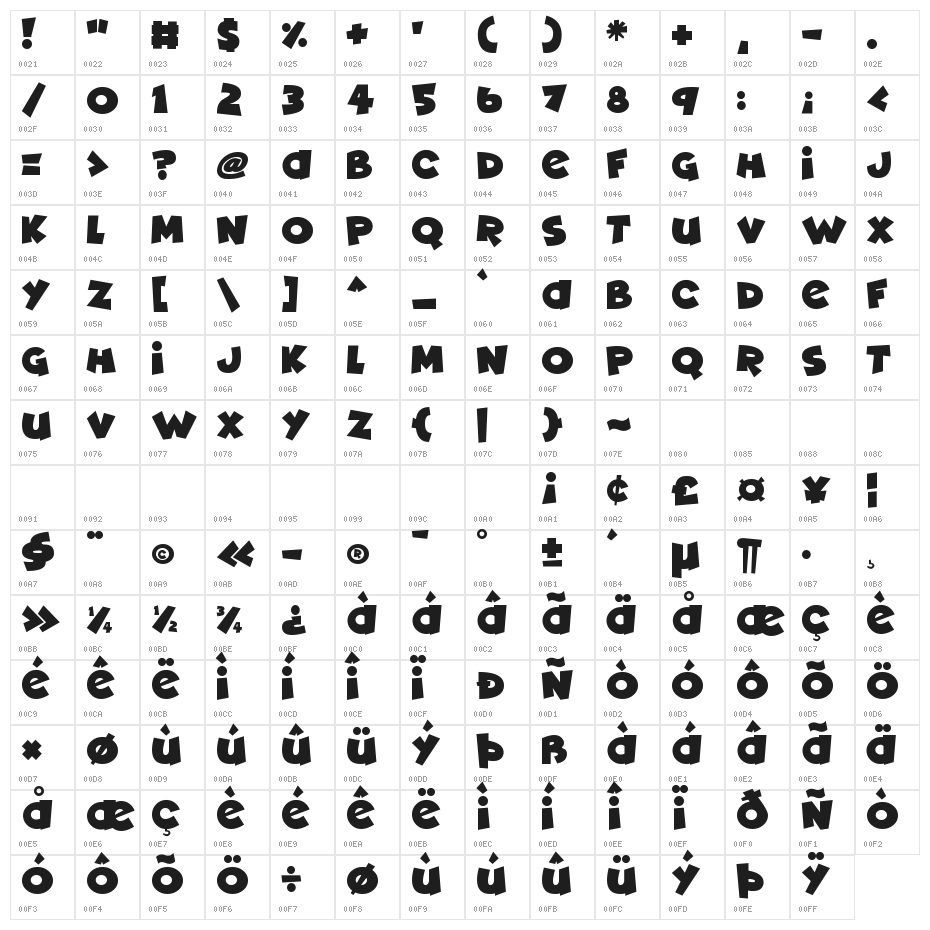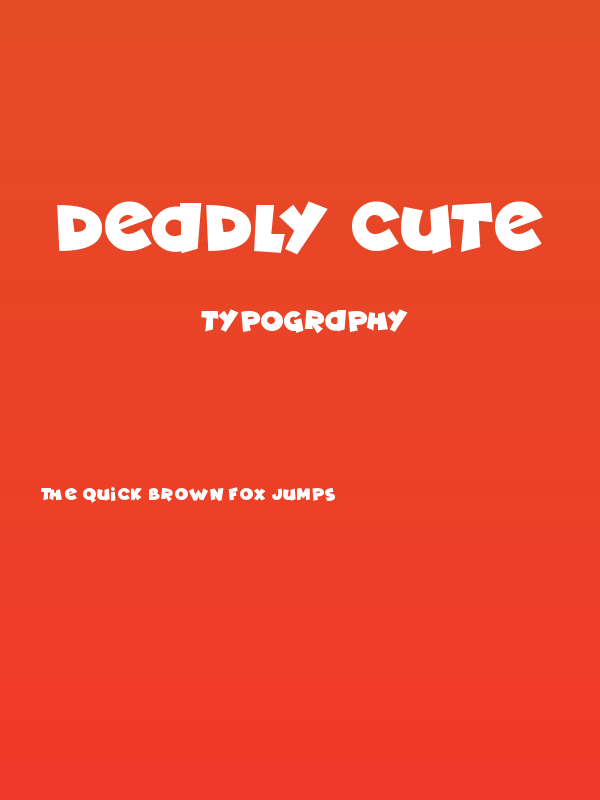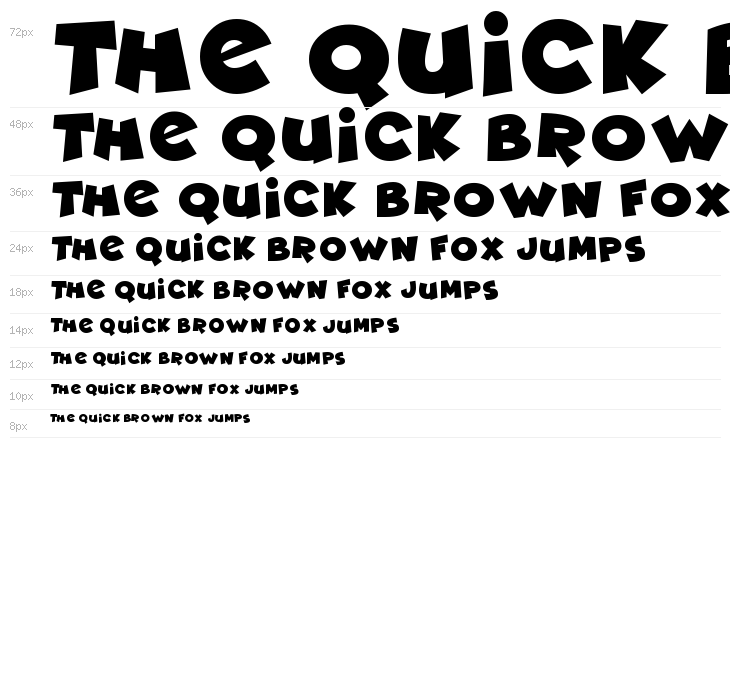
Deadly Cute Font
| Stile generale | Playful, Cartoonish |
| Progetti proposti | Ideal for children's books, playful branding, comic strips, and eye-catching posters. |